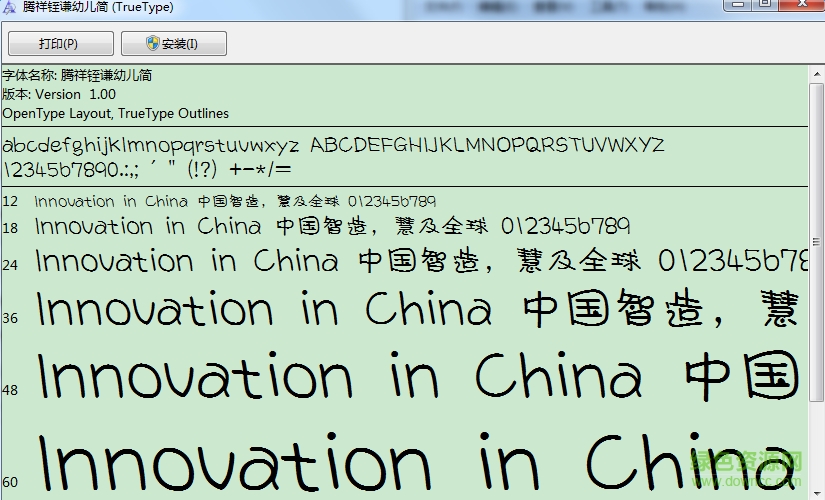
騰祥铚謙幼兒簡是一款非??蓯鄣?a href="http://kiwanis-srv.org/k/yishuziti/" target="_blank">藝術(shù)字體,這款字體類似手寫字體,字體字形圓潤,清新脫俗,整體效果非常出色,喜歡那就來本站下載體驗吧!
此款字為POP手繪字體.由資深硬筆書法家、手繪pop創(chuàng)意設(shè)計師高铚謙手繪完成原字稿.整幅字風(fēng)格統(tǒng)一、行文規(guī)整,粗看似幼兒寫字歪歪斜斜,仔細(xì)看整個版面卻個性鮮明、極具功力.字里行間充滿童真稚趣,彰顯活潑靈動的個性.本作品可用于出版印刷、廣告設(shè)計、網(wǎng)頁設(shè)計、包裝設(shè)計、屏幕顯示、手機顯示等.